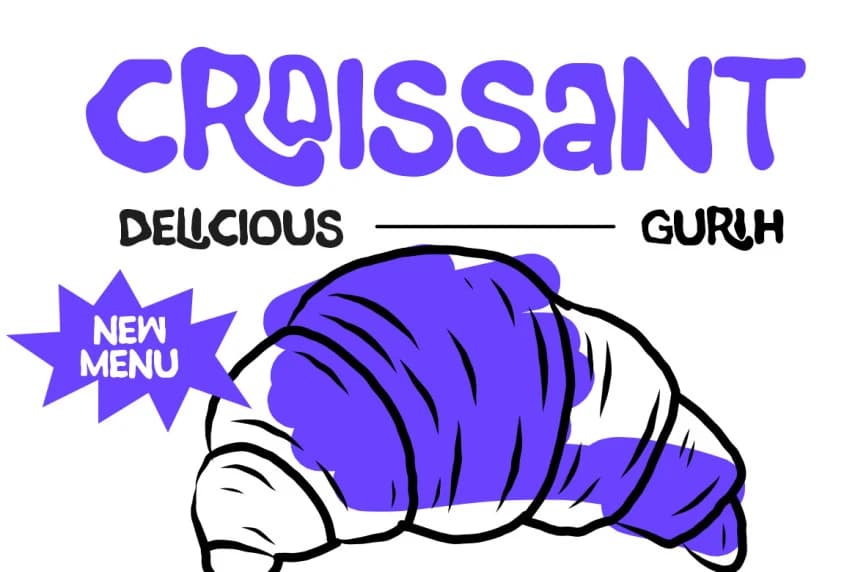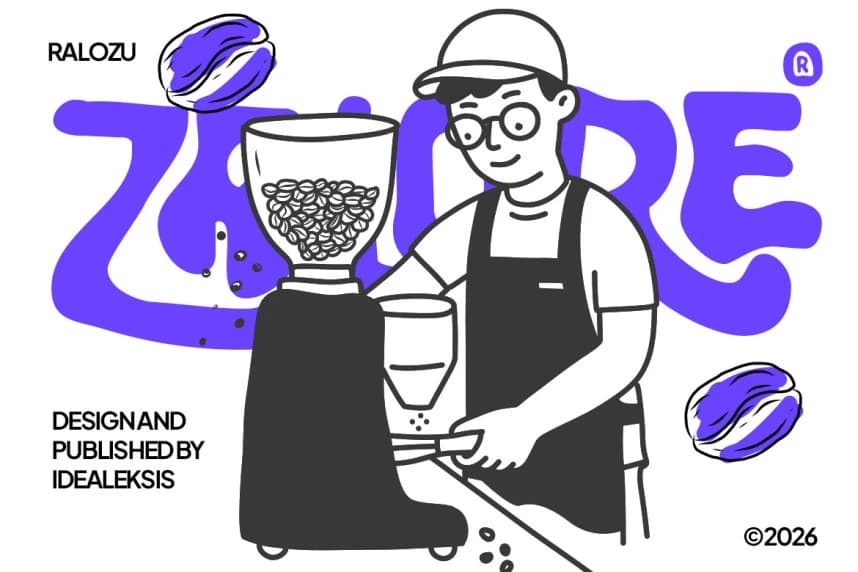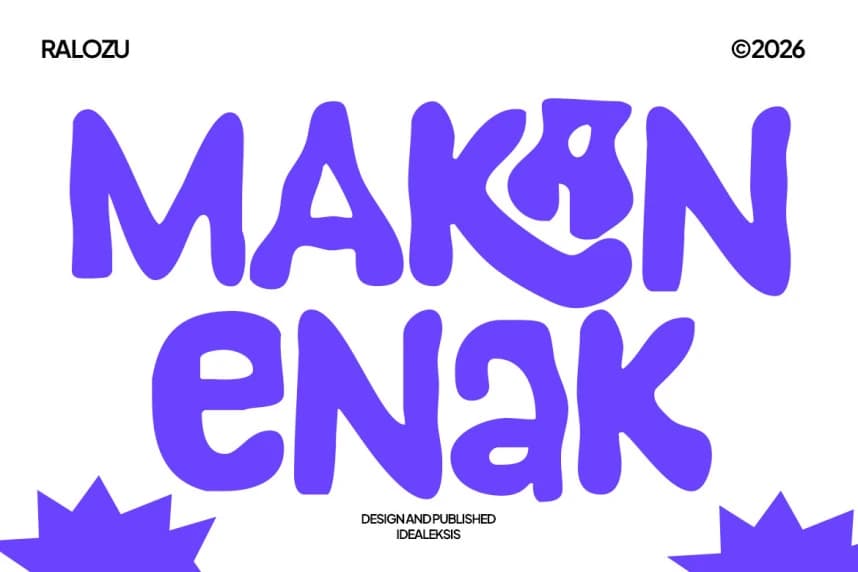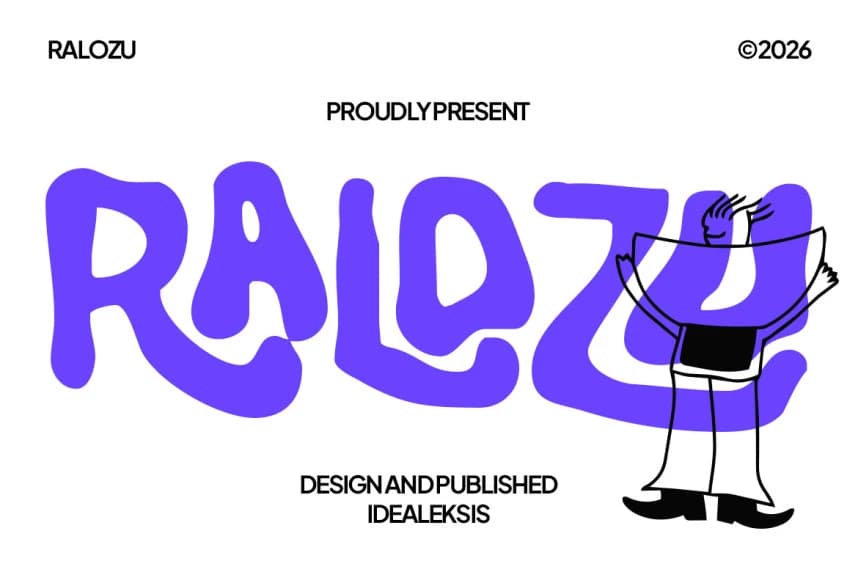
Ralozu – Food Font, dinamik ve sanatsal bir hava taşıyan kalın, dalgalı bir gösteri yazı tipidir. Kalın ve dalgalı harf biçimleri ritim ve hareket duygusu yaratır; metne oyunbaz ama çarpıcı bir varlık kazandırır. Fontun akıcı kıvrımları ve canlı kişiliği, yaratıcı afişler için idealdir, experim
Ralozu – Food Font, dinamik ve sanatsal bir hava veren kalın, dalgalı bir gösteri yazı tipidir. Kalın, dalgalı harf biçimleri bir ritim ve hareket hissi yaratır, metne eğlenceli ama çarpıcı bir görünüm kazandırır. Yazı tipinin akıcı eğrileri ve canlı kişiliği, yaratıcı posterler, deneysel marka tasarımı ve eğlence ile özgünlük hissi veren tasarımlar için idealdir.